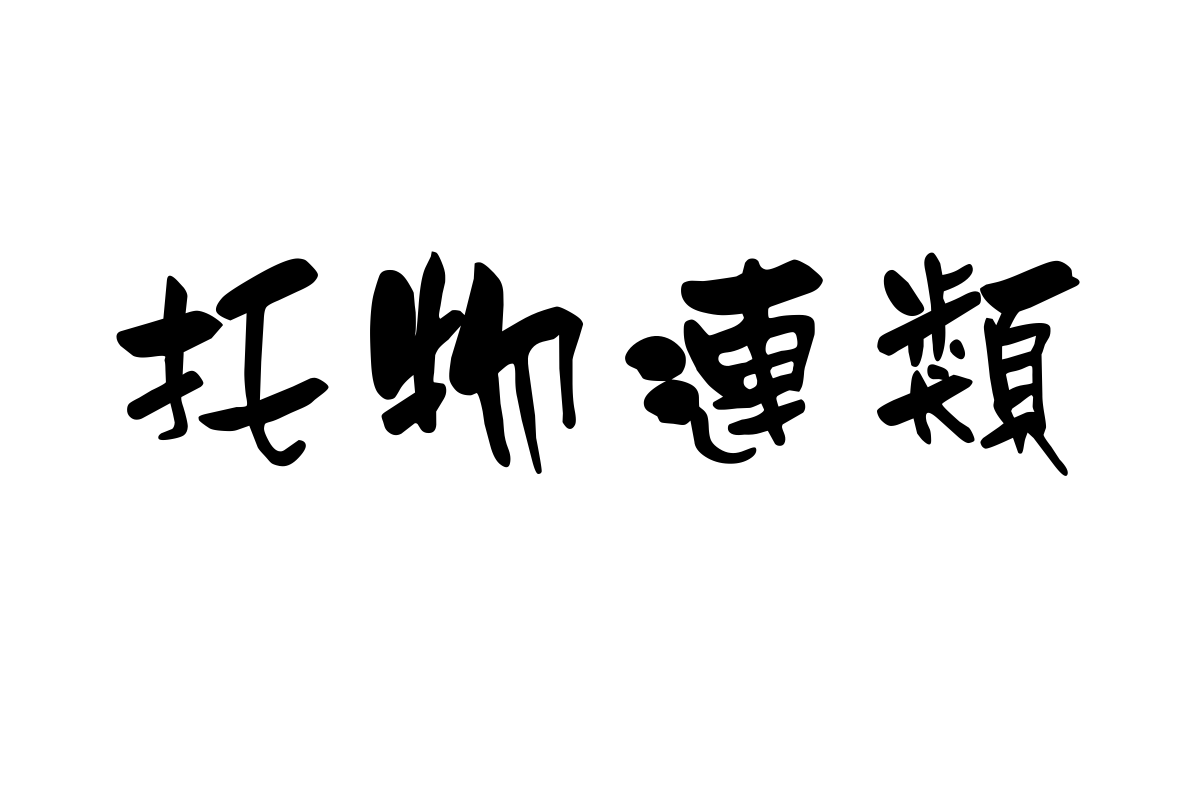
汉仪凌波体是一套中文字体,由汉仪字库设计。这套字体以其独特的风格和美感,深受广大设计师和用户的喜爱。
汉仪凌波体的特点主要体现在以下几个方面:
1. 字形优美:汉仪凌波体的字形线条流畅,结构紧凑,给人一种优雅、灵动的感觉。无论是书写还是印刷,都能展现出优美的视觉效果。
2. 字体多样:汉仪凌波体包含了多种不同的版本,如简体、繁体、日文等,满足不同场景的需求。用户可以根据自己的需要选择适合的版本进行使用。
3. 适应性强:汉仪凌波体适用于各种应用场景,如广告、包装、报纸、杂志等。它的适用范围广泛,能够满足不同行业的需求。
5. 支持矢量化:汉仪凌波体支持矢量化,可以应用于网页设计、图形设计等领域。这使得用户在制作海报、宣传册等平面作品时,能够更加自由地发挥创意。
总之,汉仪凌波体是一款功能强大、美观大方的中文字体。它不仅适用于各种应用场景,而且易于使用,能够满足不同用户的需求。